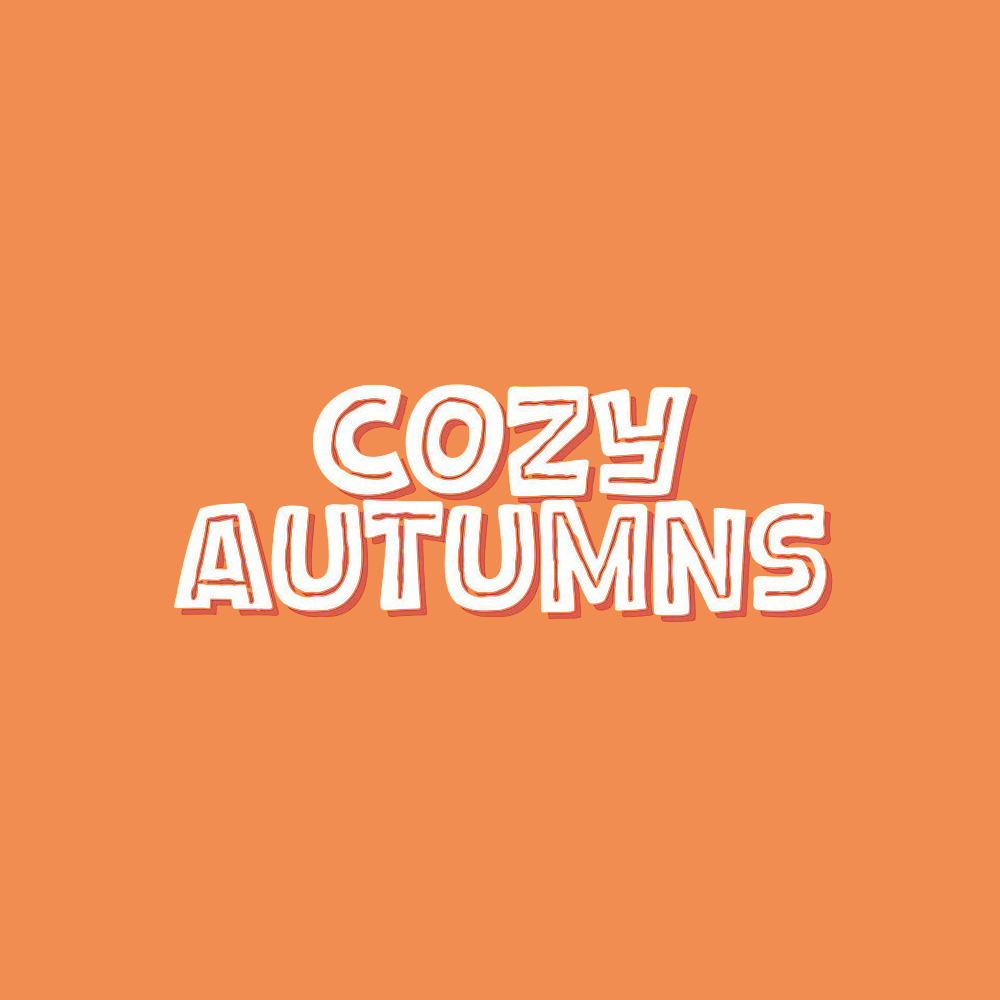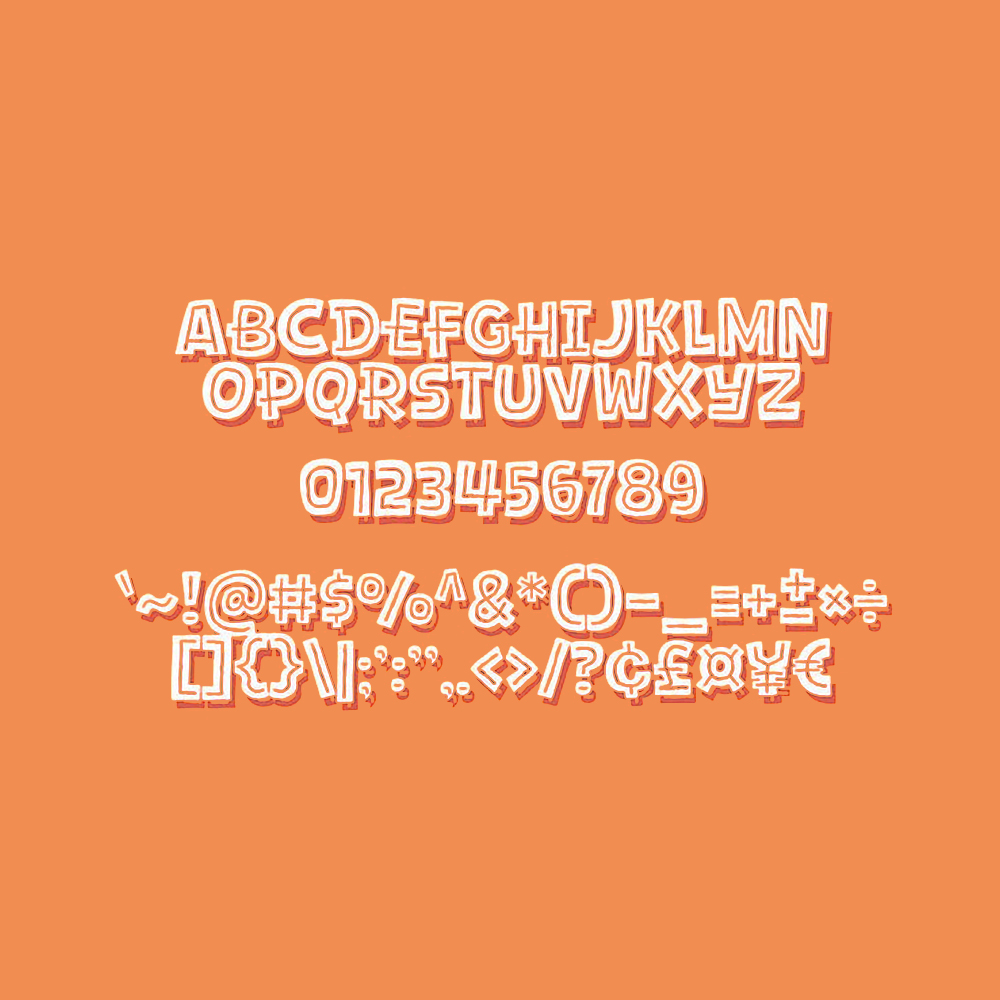
دانلود فونت انگلیسی Cozy Autumns Font
فونت پرمیوم و انگلیسی Cozy Autumns Font یک فونت نمایشی جسورانه و دستساز با جذابیت روستایی و شخصیتی بازیگوش است. خطوط بافتدار و خطوط نامنظم آن، حس دستساز بودن را به آن میدهد و آن را برای پروژههای فصلی، پوسترها و برندسازی خلاقانه ایدهآل میکند. سبک لایهای منحصر به فرد این فونت، با جلوه سایهای ظریف، ظاهر گرم و دوستانه آن را افزایش میدهد و برای بستهبندی، جلد کتاب یا تیترهای چشمنواز ایدهآل است. سبک رسای آن، روح پاییز و طرحهای دنج را به تصویر میکشد. Cozy Autumns با لمس دستساز جذاب خود، به هر پروژهای گرما و شخصیت میبخشد.